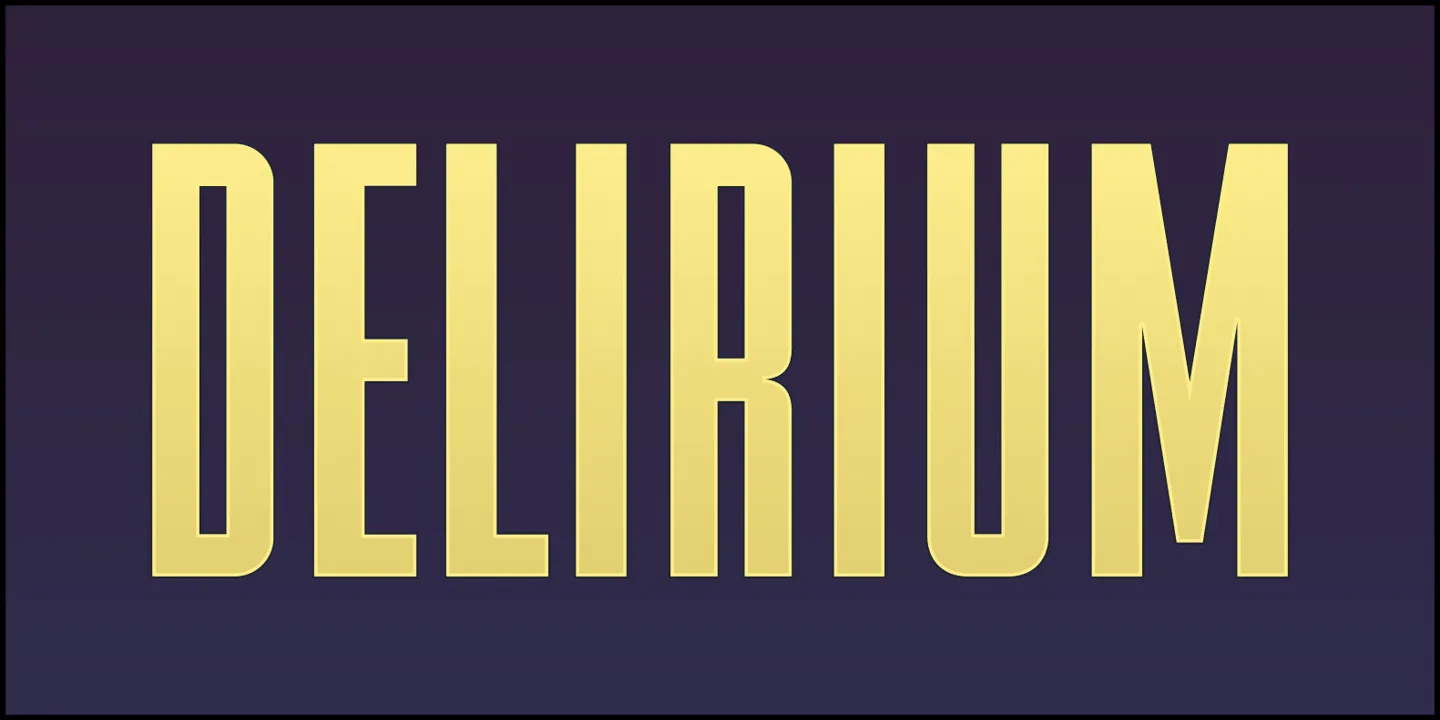
FTY DELIRIUM - это узкий, готический, газовый шрифт с винтажным видом, стойкой и чувством. Неоновый инлайн-эффект был добавлен к базовому весу DELIRIUM для повышения его универсальности. Неоновый эффект можно даже применить как два отдельных элемента, используя меню стилей шрифта, чтобы создать простой вариант наслоения, позволяющий использовать два цвета. Для поддержки более тяжелых шрифтов DELIRIUM и DELIRIUM NEON были добавлены дополнительные вторичные шрифты. Эти легкие шрифты идеально дополняют основные шрифты, позволяя использовать более тонкую версию DELIRIUM для завершения ваших макетов без необходимости искать дополнительные шрифты.